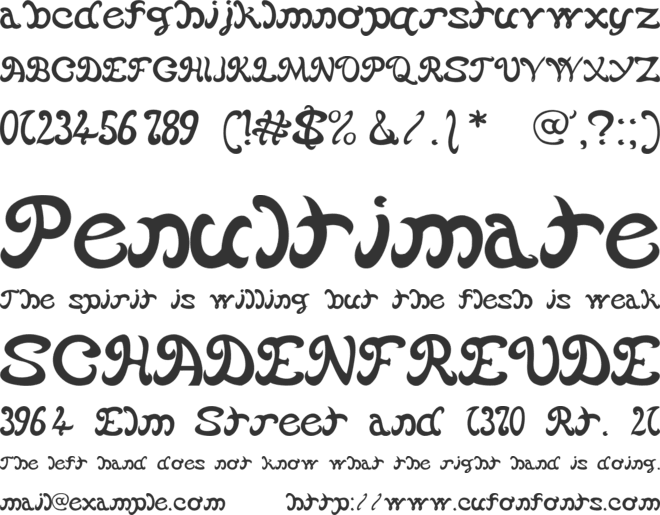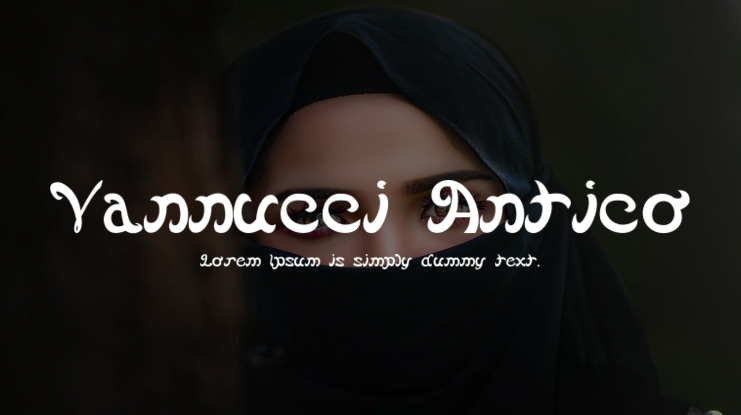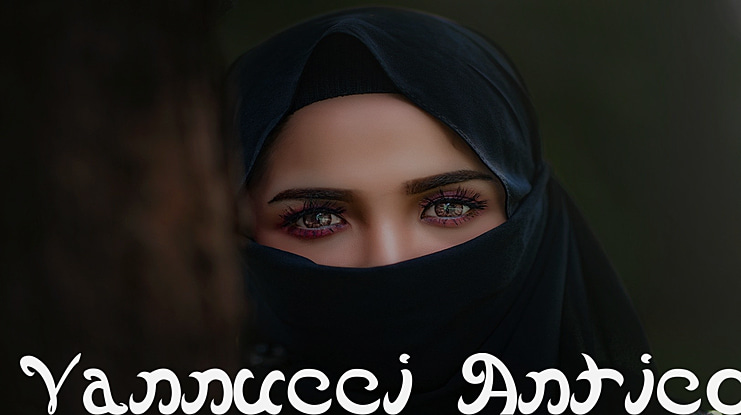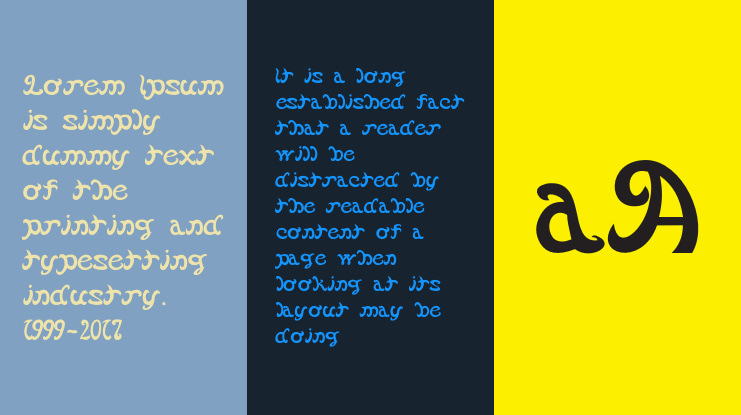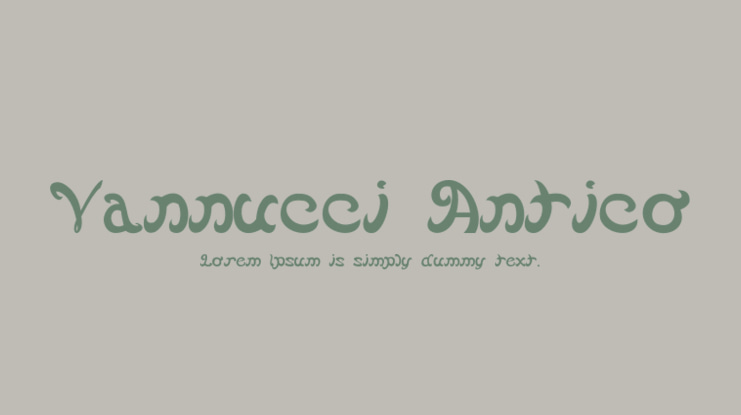
Vannucci Antico Font Family
P. A. Vannucci
VANNUCCI ANTICO font: Dalla tradizione e dall'amore trasposto nei grandi pittori della scuola italiana, un font inedito che unisce l'estro e il virtuosismo del carattere ornamentale e decorativo, dedicato a Pietro Vannucci.